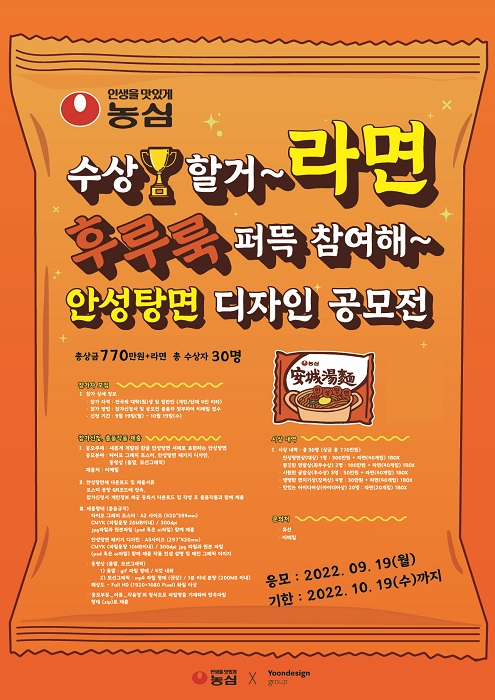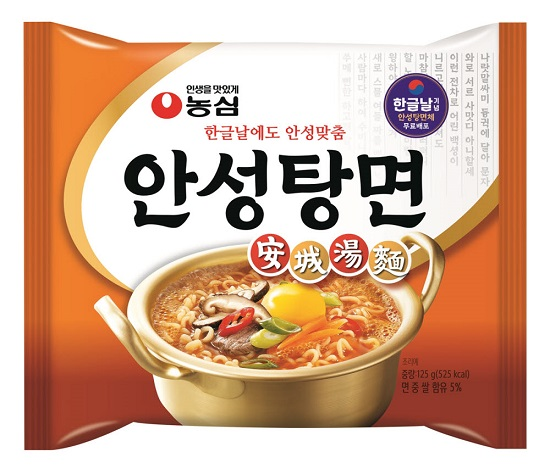
㈜윤디자인그룹, 농심 안성탕면체 활용한 타이포 그래픽 공모전 진행
[문화뉴스 김국진 기자] 타이포 브랜딩 전문기업인 윤디자인그룹은 다음달 19일까지 새롭게 개발된 한글 안성탕면체를 활용한 타이포 그래픽 공모전을 진행한다고 19일 밝혔다. 이번 공모전은 농심이 주최하고 윤디자인그룹이 주관한다. 공모전에 참여하려면 농심 홈페이지 내 안성탕면 한글날 이벤트 페이지에서 안성탕면체를 내려받아 창작한후 오는 10월 19일 오후 6시까지 이메일로 제출하면 된다.
㈜윤디자인그룹 담당자는 “안성탕면체는 안성탕면 로고의 특징을 반영해 담백함이 묻어나는 네모꼴 서체로 개발한 것이 특징이다. 붓글씨 스타일로 디자인한 안성탕면체는 한 획에서 다양한 굵기를 표현함으로써 생동감과 입체감을 주었고, 마무리는 시원하게 뻗어 고전적이면서 긍정적인 느낌이 나도록 했다. 잉크 사용량을 줄이는 ‘ECO체’도 함께 제작해 친환경 트렌드에 맞게 제작되었다.”며 “이번 공모전을 통해 안성탕면체를 활용한 다양한 타이포 그래픽 작품들을 기대한다”고 밝혔다.